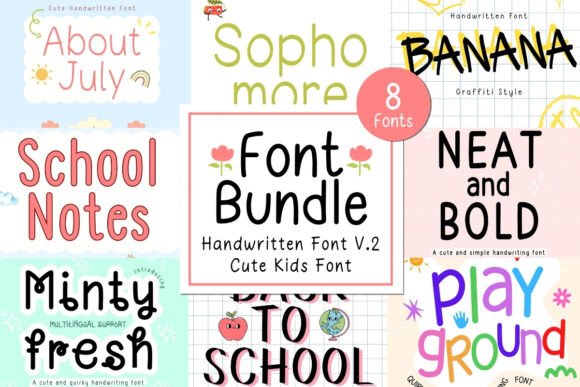
Neat & Clean Handwritten Bundle V.2
Nếu bạn đang tìm kiếm các tài nguyên chất lượng cao như Neat & Clean Handwritten Bundle V.2, gói cao cấp này là một lựa chọn tuyệt vời cho các dự án sáng tạo của bạn.
Cho dù bạn đang tạo sản phẩm POD (In theo yêu cầu), thiệp mời đám cưới hay đồ họa mạng xã hội, Neat & Clean Handwritten Bundle V.2 đều là một sự lựa chọn lý tưởng.